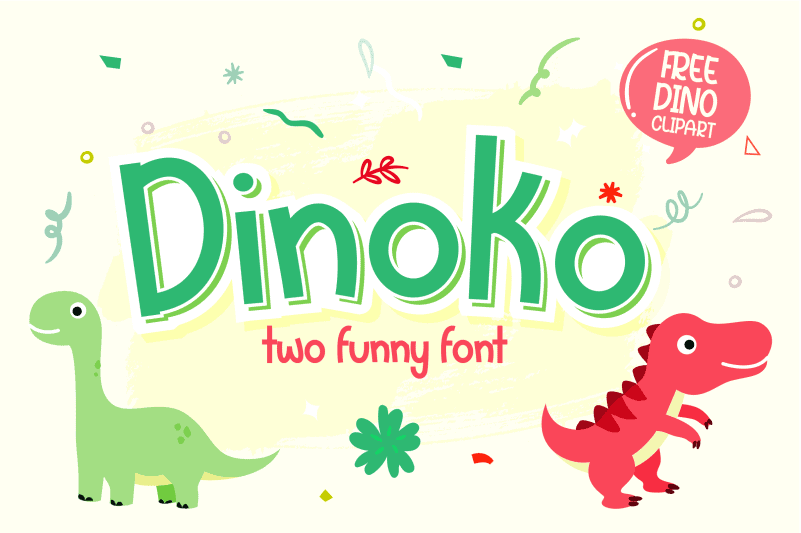
Dinoko Display Font – Fonte Grátis
Dinoko Display Font
A Dinoko Display Font é uma fonte de exposição encantadora e despretensiosa, perfeita para aqueles que buscam algo único no seu design digital. Esta elegante escolha para a tipografia traz um toque incrivelmente alegre aos seus projetos criativos, destacando-os do resto da concorrência com sua forma divertida e versátil. Seja você designer gráfico ou criativo, adicionando esta bela fonte de exposição a seus projetos certamente irá tornar suas ideias originais mais memoráveis e cativantes.